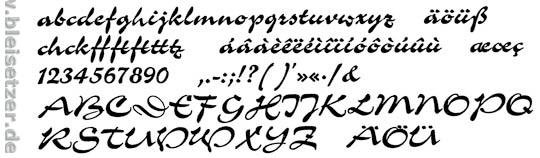
handgeschr. Werbeschriften - keiner weiss, wo es die gibt..
Im Rahmen einer Untersuchung der (West)Berliner Kneipen- und Werbeschilderwelt treffe ich immer wieder auf Schriften, die ich in digitaler Form noch nie gesehen habe. Wer mir da weiterhelfen kann, bekommt von mir ein Lob und Anerkennung..
Man darf bitte nicht vergessen:
Neben den Typographen, die für den Print-Bereich tätig waren, gab es noch eine zweite Produktionsschiene der Schildermaler. Das war ein Lehrberuf.
Ein Schildermaler, der sich freihand betätigt, ist nicht gebunden an bewegliche Lettern. Hier ist tatsächlich bei der Verwendung auch heutiger, moderner "Plakat- oder Pinsel-Schriften" die moderne Technik eingeschränkt.
Interessant im Bezug auf die Schildermaler:
Jan Tschicholds »Meisterbuch der Schrift«